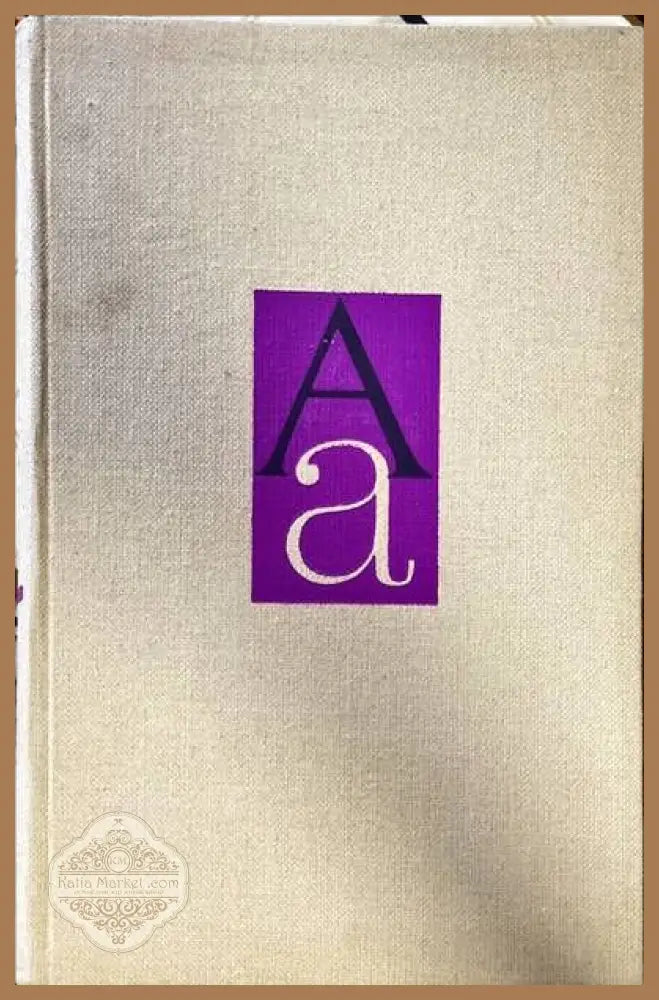
Шрифтът през вековете - Васил Йончев
Шрифтът през вековете (1289) е архиважно антикварно издание, което отвежда читателя назад през историята на типографията и графичния дизайн. Това твърдо подвързано издание от 1974 г., автор Васил Йончев, издадено от Български художник, предлага дълбок поглед върху еволюцията на шрифта през различни епохи и култури, с акцент върху българския контекст и значимостта на кирилицата в световната графична традиция.
Защо това издание е уникално
Този том не е просто компилация от шрифтове. Той предоставя контекстуален преглед на стилове и техники, които са оформили начина, по който пишем и печатаме днес. Васил Йончев подчертава историческите връзки между руни, калиграфия, латиница и кирилица, като създава смислен надпис за това как различните култури са взаимодействали в развитието на писмеността. За колекционери и ценители на антикварни книги това издание представлява редкият компромис между академична изчерпателност и обсебваща визуалност на типографските експонати от различните епохи.
Какво може да добави към вашата колекция или проект
Читателят получава не само знания за историческия развой на шрифтовете, но и практическа перспектива за тяхното влияние върху днешния графичен дизайн. Този том е подходящ като основа за курсови задачи, изложби за визуална култура и визуален анализ на човешката писменост през вековете. За всеки, който се занимава с типография, калиграфия или библиография по изкуство и култура, това издание предлага дълбоки размишления и конкретни примери, които често липсват в съвременни обзори на темата.